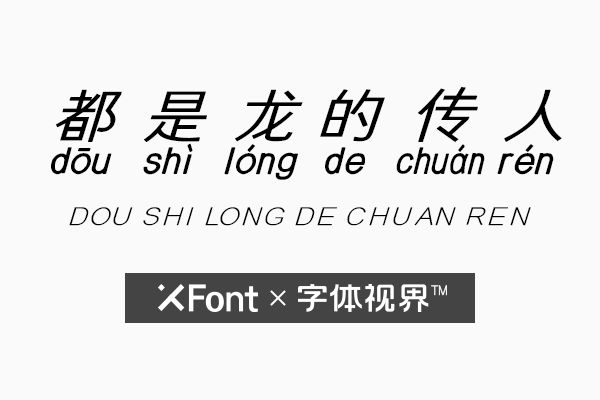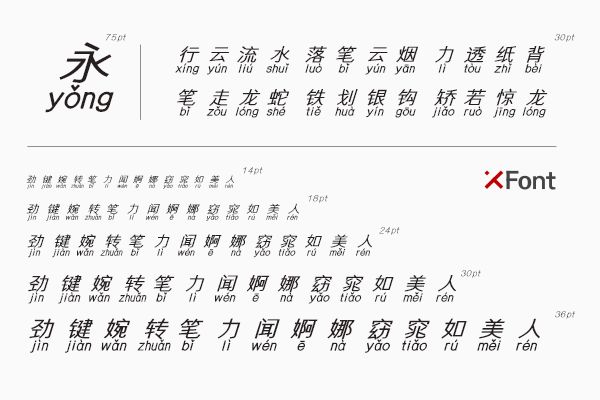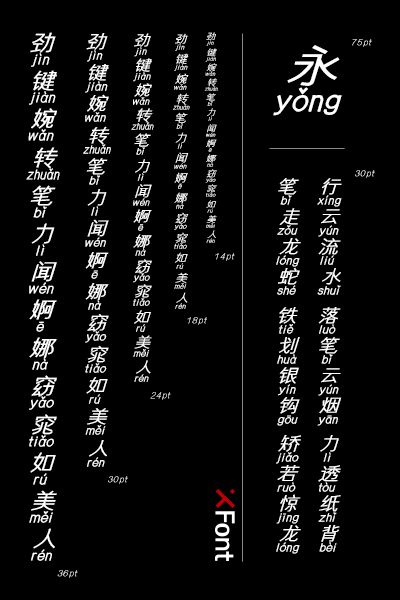
都是龙的传人字体,体现满满爱国情怀的字体设计。
《龙的传人》这首歌本是由侯德健所创作,这首歌诞生之后的传播经历了不少坎坷的磨难,后由王力宏改编传唱,有趣的改编赋予了这首歌不一样的生命力,《龙的传人》以超越政治、超越时空的高度,再现出中华民族的精神和感情。
在都是龙的传人这款字体中,设计师把“方正”的这一特点放大化,在字体外圈规画了一个正方形格子,想尽办法让字面尽量平铺,让字体笔画分别向四个角落进行延展。
在做到向四角延展的同时还要结合字体本身的字形特点,不能盲目地拉伸,为此设计师认真研究适合每个字的设计方法。同时,设计师使用笔直的笔画线条,笔画的转折角度多数为90度的直角,使字体更加“方正”。
一般的拼音体结构是拼音在上,字体在下。与一般的拼音体不同,这款都是龙的传人字体的拼音被设计师安排在了字体的下方,特点鲜明,令人眼前一亮。
另一个创新的点是在方正化字型之后,设计师却对整个字体进行了倾斜的改动,使字体产生自右上-左下角度的倾斜,改变了大家对汉字的刻板印象。
这款“都是龙的传人”创新性强,这也是设计师对当代龙的传人所寄予的希望,只有创新才能更好地发展。